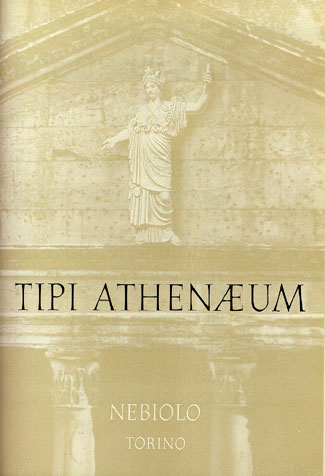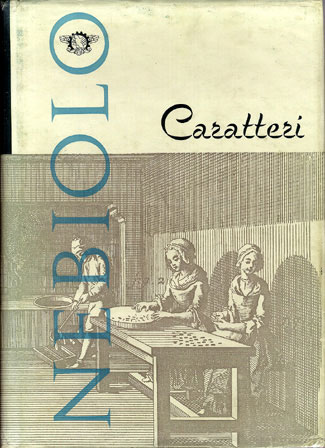
Aldo Novarese (1920-95)
Typeface designer italiano que produziu alguns tipos «clássicos» do século xx. Foi um dos mais prolíficos desenhadores, tendo criado um total de 76 fontes, desdobradas em 218 cortes e pesos. Entre as mais usadas, estão fontes como a Eurostile, a Stop, e a ITC Novarese
Aldo Novarese nasceu em 1920 em Pontestura, Piemonte. Cursou a Scuola Artieri Stampatori em Turin0, uma escola para impressores. Aí aprendeu tipografia, litografia, gravura em cobre e xilogravura. Seguidamente cursou a Scuola di Tipografia GB Paravia, uma escola de tipografia, para a qual viria a regressar depois da Segunda Guerra Mundial - para leccionar a Estética da Tipografia. Em 1936, começou os seus estudos no Estúdio Artístico da Fondazione Caratteri Nebiolo em Turino, onde passou quase 40 anos da sua carreira criativa. Em 1938 ganhou uma medalha nos Ludi Juveniles do governo fascista italiano. Esta medalha acabaria por salvar-lhe a vida, quando foi imprisionado por participar em protestos contra a Guerra. Mais tarde integrou os partisani, as forças armadas da Resistência anti-fascista, que lutou contra as tropas alemãs. Estas experiências marcaram-no para o resto da vida. Depois de ter leccionado Tipografia numa Escola de Design, passou a trabalhar para a Fundição Niebolo, onde exerceu as funções de director artístico. A partir de 1972, passou a trabalhar como freelancer. O mais conhecido tipo de Aldo Novarese será a fonte Microgramma, de certa maneira definindo um Modernismo italiano.
Microgramma foi concebida com uma fonte moderna não no sentido histórico, mas moderno no conceito do século XX: streamlined, clean, sleek, stripped to its essentials. É uma fonte sem serifa construída à volta de um quadrado (ou rectangulo) com os cantos arredondados. A Microgramma foi criado como um alfabeto versal; posteriormente foi acrescida de minúsculas por Novarese, passando a chamar-se Eurostile. Outras criações de Novarese são o seu Egizio, inspirado nas serifas-grossas do século XIX. A Nova Augustea (1951), ITC Novarese, Garaldus (fins do decénio de 1950), Recta, Magister (1966, Nebiolo), Forma, Mixage, ITC Fenice. Fonderia Caratteri Nebiolo, hojeSocieta Nebiolo
ExposiçõesIl segno alfabetico Dicembre 1988 Galleria Aiap viale Col di Lana 12, Milano. Una mostra in ricordo di Aldo Novarese. Lo sfondo della vita di Aldo Novarese è fatto di immagini: autoritratti, architetture, paesaggi, figure, nature morte, segni astratti, segni alfabetici, fissati con genialità in tantissimi espressivi disegni, quadri, ritratti con tutte le tecniche immaginabili, compresa la fotografia. Ma il vero Aldo Novarese che tutto il mondo ha conosciuto e ammirato è il Novarese progettista e disegnatore di caratteri da stampa. La mostra, originariamente allestita presso i Portici del Lingotto a Torino, dal 15 maggio al 20 giugno 1998 è stata promossa da Progresso Grafico con il patrocinio della Provincia di Torino, del Politecnico di Torino e dellAiap, curata da Piero De Macchi. Aldo Novarese, giovanissimo, che si era già distinto per le sue attitudini durante i corsi presso la Scuola tipografica, viene chiamato da Alessandro Butti, allora direttore dello Studio Artistico Nebiolo, come diretto collaboratore. Nel 1952 si trova a dirigere lo Studio, e si impegna subito a sviluppare progetti in molte direzioni. Deve corrispondere alle esigenze commerciali, che gli vengono segnalate dalla direzione Nebiolo, ma ciò non gli impedisce di esprimersi con estro e genialità. Degli anni Cinquanta sono il Garaldus, importante classico per testi editoriali, il Juliet, garbato corsivo inglese, il Cigno, elegante scritto, il progetto Recta, ricchissimo di variazioni seriali, l'Egizio che lo impegna per ben quattro anni, e poi fantasie come Slogan, Ritmo, Estro. Aldo Novarese in questi anni si inserisce con entusiasmo negli annuali Rencontres de Lure, polo di interesse internazionale, dove convergono da tutto il mondo i migliori professionisti del carattere e della tipografia, con i quali scambia esperienze e discute problemi. Queste esperienze fanno sì che il suo lavoro sia notato da molti ambienti professionistici all'estero. Nel 1957 Novarese propone una sua classificazione degli stili dei caratteri tipografici, improntata a quella presentata da Maximilien Vox nel 1955. La sua attività presso la Fonderia Caratteri Nebiolo prosegue intensamente. Del 1962 è l'Eurostile, derivato dal Microgramma di Butti, completato del minuscolo e di nuove serie, che riscuote un grande successo internazionale. Nel 1966 viene prodotto il Magister, e un anno dopo il Metropol e l'aperto e leggibile Oscar. Nel 1968, anno in cui disegna un altro scritto l'Elite, si sperimenta in Nebiolo un lavoro di équipe con un team di grafici, per integrare i progetti con le valutazioni dei fruitori. Nasce così il Forma, dal disegno fluido e accurato. che però sul piano commerciale non riesce a sfondare la massiccia presenza dei concorrenti Univers ed Helvetica. Con la stessa impostazione di lavoro viene disegnato il Dattilo, dal ritmo rotondo e luminoso, tecnicamente perfetto. Del l978 è lo Stop, il meno "tipografico" degli alfabeti di Novarese, forte e geniale sintesi del segno alfabetico. Con il 1978 si chiude un'epoca: il piombo è stato definitivamente superato dalle tecniche di fotocomposizione e l'informatica, ancor più flessibile, è alle porte. La Fonderia Caratteri Nebiolo, all'età di cento anni esatti, cessa la sua attività. Immediatamente Aldo Novarese riceve richieste di collaborazione da ogni parte del mondo. Ha inizio così la sua attività free lance, che gli consente di pubblicare moltissimi lavori di successo, e di estendere molto lontano la sua notorietà. Una classifica giapponese gli ha assegnato il primo posto per numero di caratteri prodotti. Sono veramente moltissimi (circa 200), e non si può qui ricordarli tutti. Ma bisogna citare almeno i principali: il Novarese, originalissimo nel corsivo, perché ne riprende la matrice cancelleresca, la quale anticamente conservava in tondo le lettere maiuscole (capitalis romana). Poi il Fenice, di grande successo internazionale, perfetta dimostrazione delle capacità stilistiche e tecniche di Aldo Novarese. Il Symbol, un'idea semplicissima per un grande risultato. Il Mixage, che riesce, insieme al bellissimo Delta, a dire ancora una parola nuova nella ramificatissima progenie dei lineari. E ancora il Nadianne, dove Novarese riesce a fondere il ritmo delle antiche cancelleresche con l'agilità quasi sensuale di uno scritto nitido e deciso. Bisogna poi ricordare le pubblicazioni di Novarese: Alfa-beta del 1964, Il carattere del 1957 e il Segno Alfabetico del 1971 più volte ristampate e tuttora unici strumenti per insegnare le basi del design delle lettere e della tipografia. Página actualizada em 08.07.2007 |